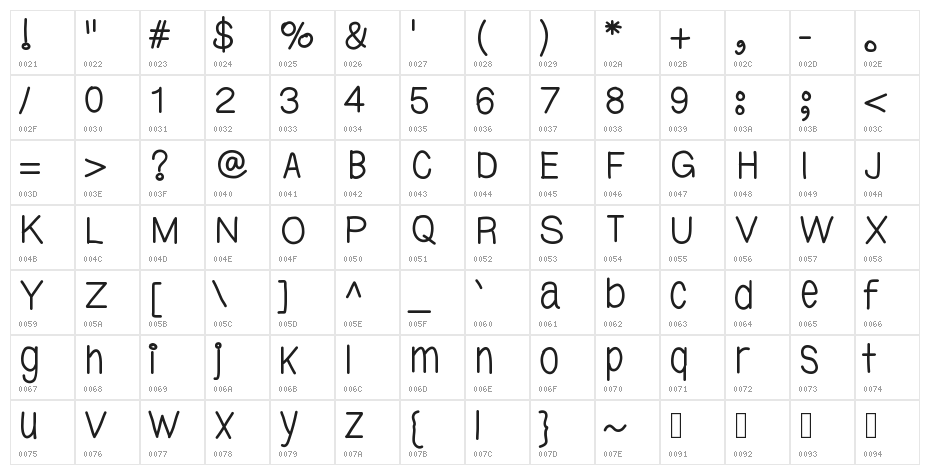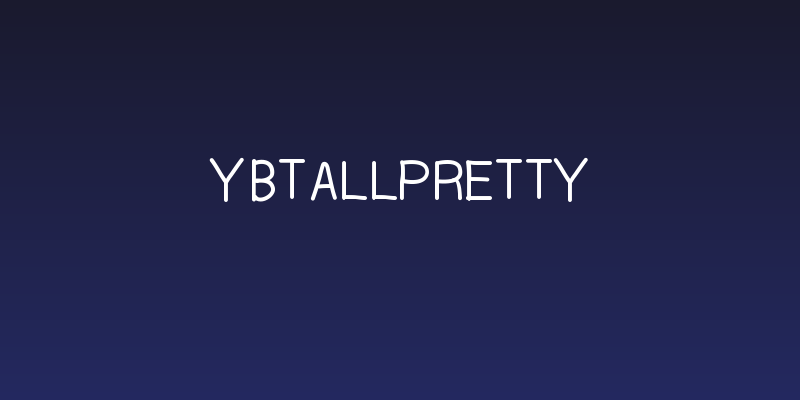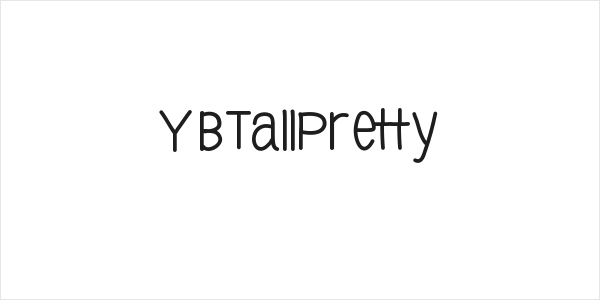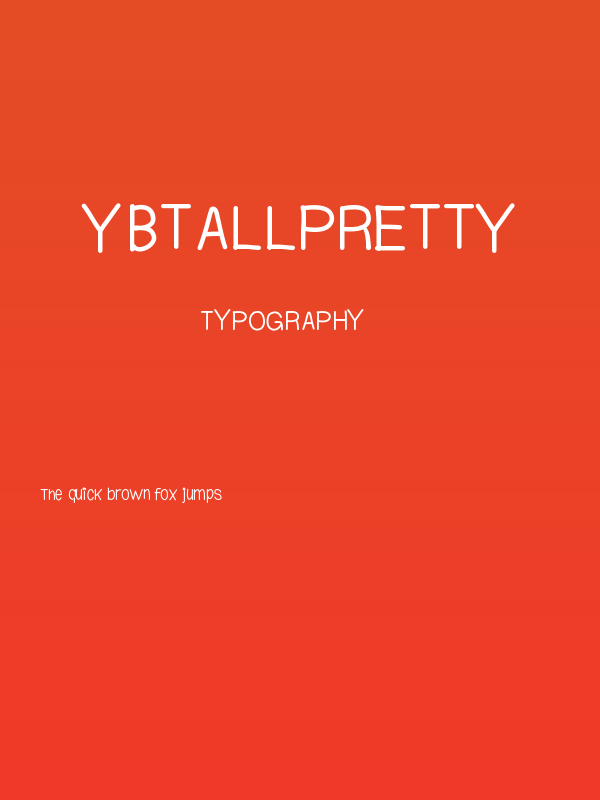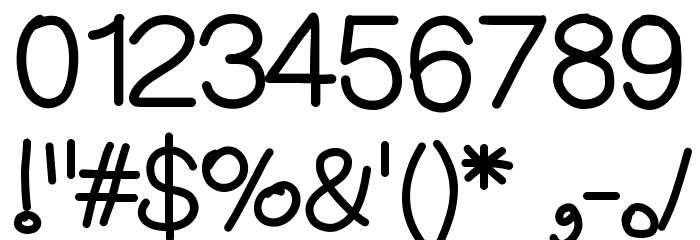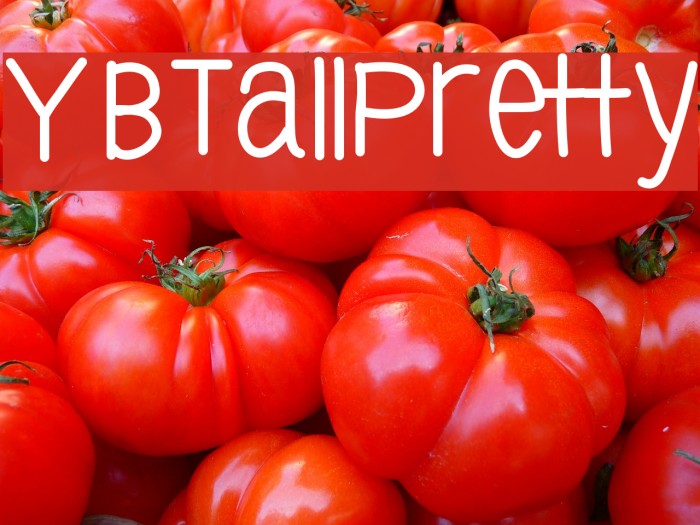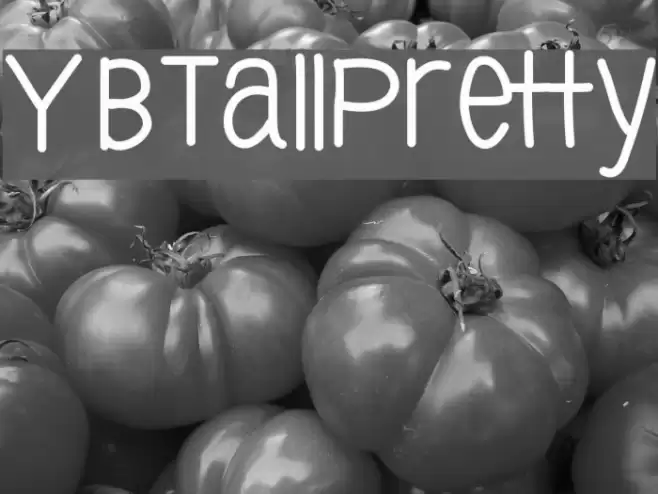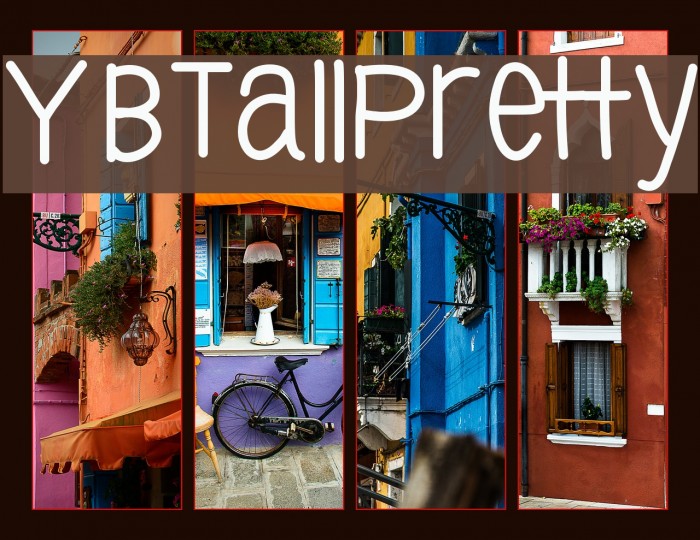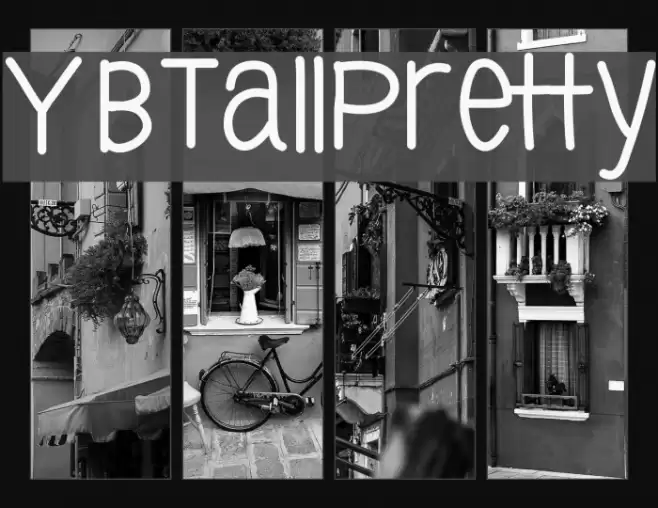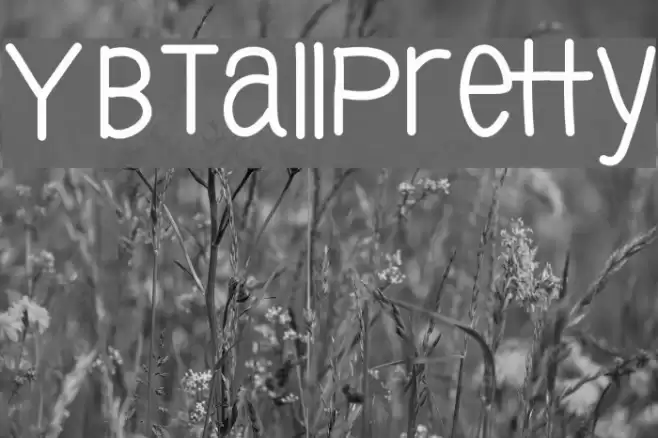
YBTallPretty Font
| Nom | YBTallPretty |
| Style général | Playful |
| Cas d'utilisation | Headlines, Logos, Casual Text |
| Projets proposés | Ideal for children's books, greeting cards, playful branding, and casual invitations. |